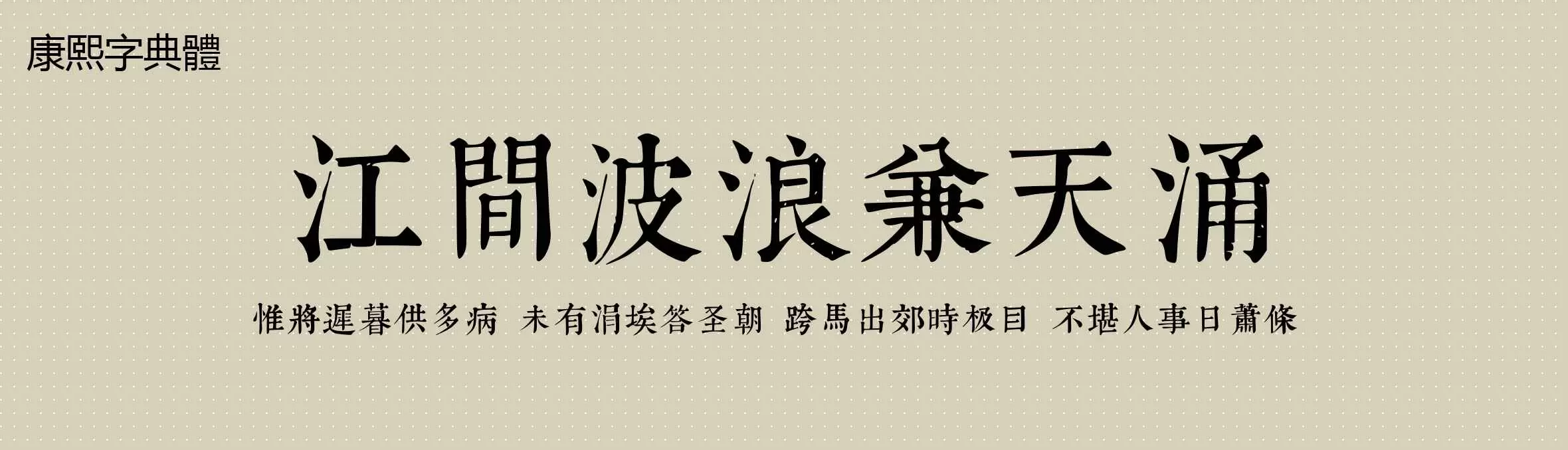
《康熙字典》是由总纂官张玉书、陈廷敬主持,修纂官凌绍雯、史夔、周起渭、陈世儒等合力完成的。该字典采用部首分类法,按笔画排列单字,全书分为十二集,以十二地支标识,每集又分为上、中、下三卷,并按韵母、声调以及音节分类排列韵母表及其对应汉字,共收录汉字四万七千零三十五个(47035个)。
康熙字典体是从古籍上影印下来的字体,其字形设计就是为了竖排服务,具有楷体的特点。